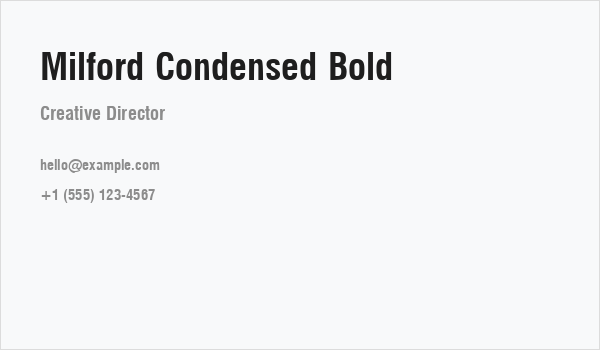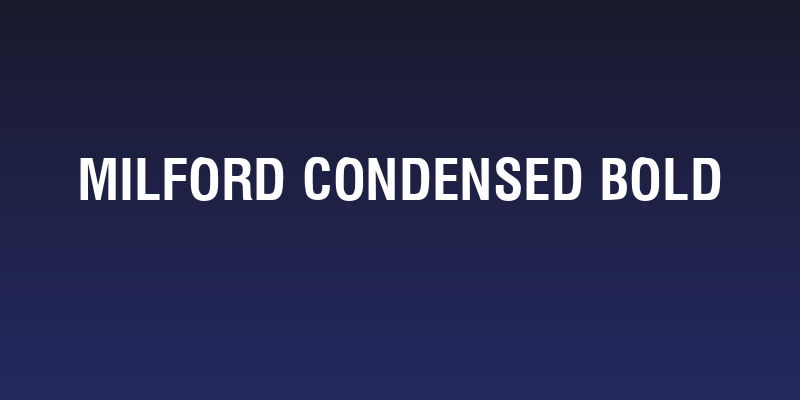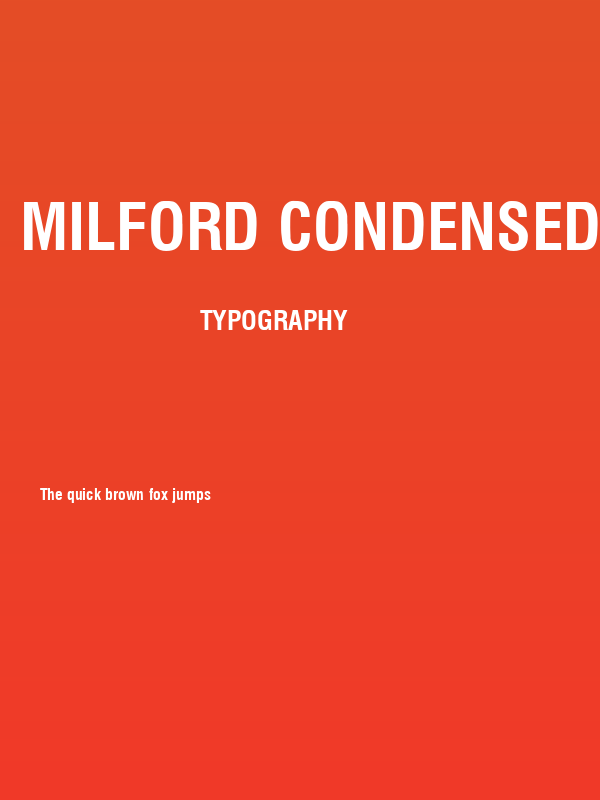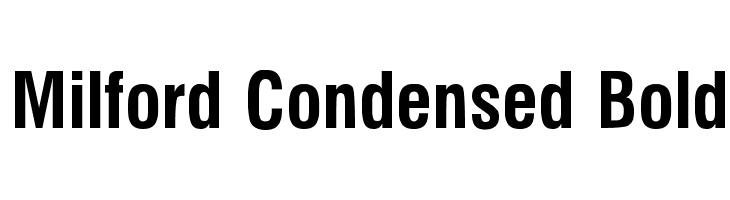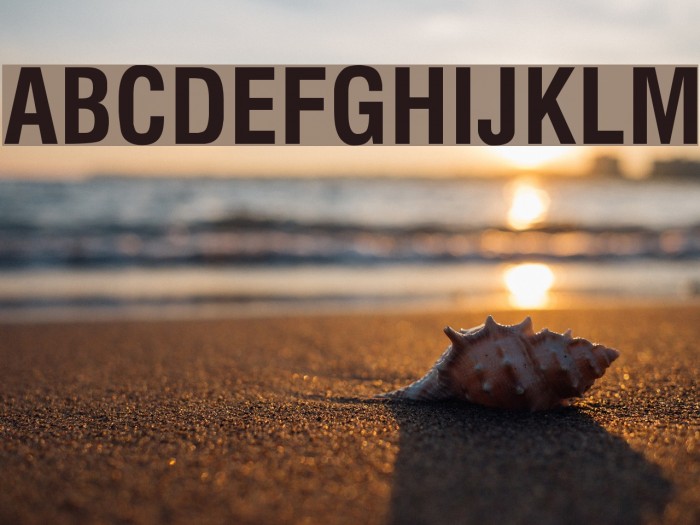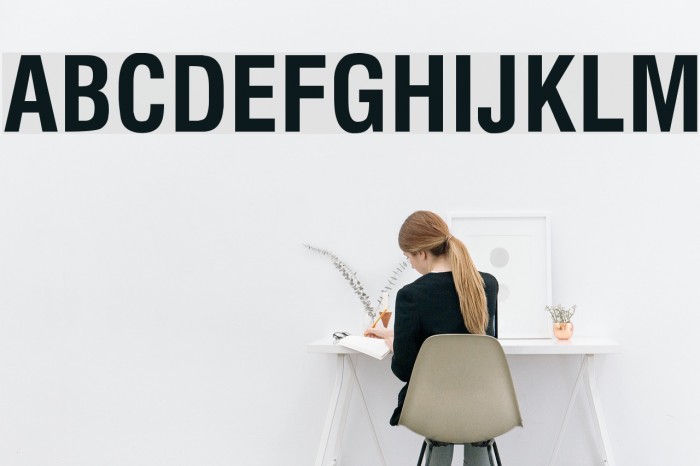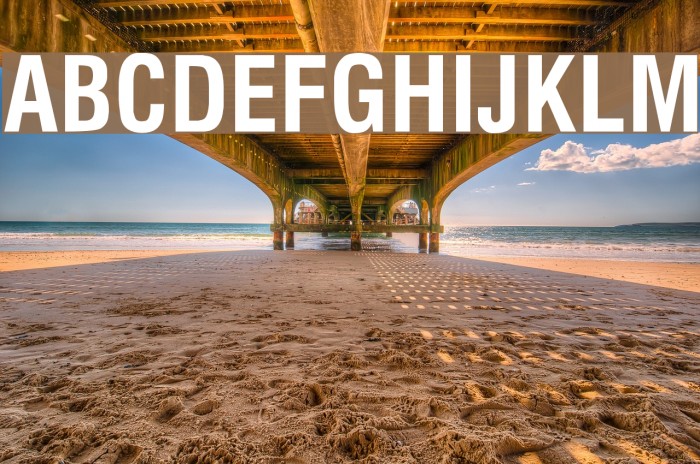
Milford Condensed Bold Font
| Cas d'utilisation | Headlines, Logos, Advertising |
| Projets proposés | This font is perfect for projects that require strong visual impact, such as posters, banners, and magazine covers. It can also be used effectively in branding and advertising materials where space is limited but emphasis is needed. |